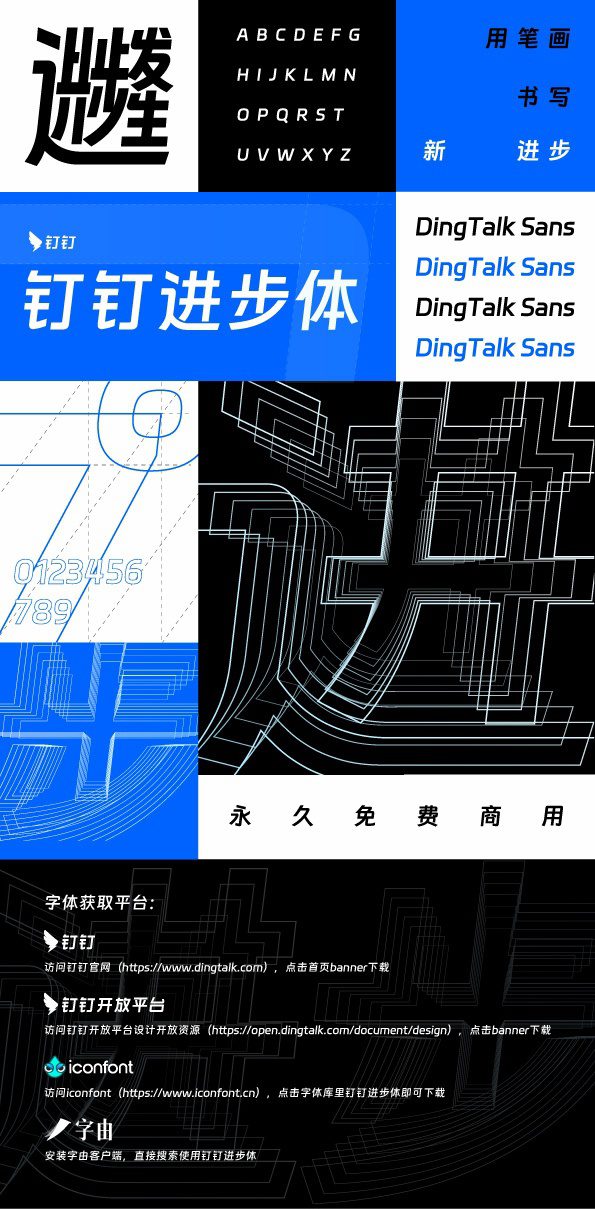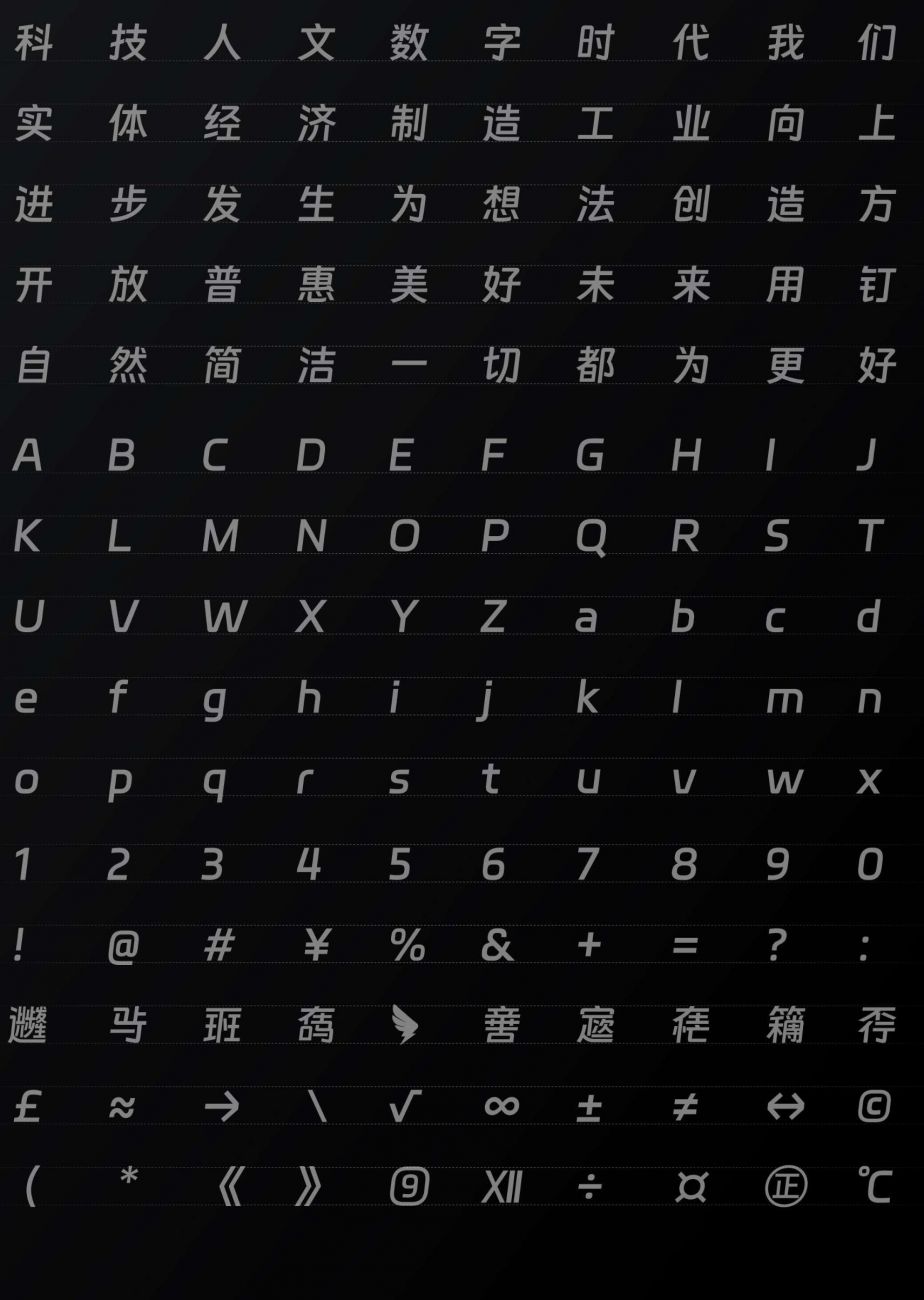
钉钉在杭州正式开启 7.0 版本产品发布会。发布会上,钉钉总裁叶军详细解读了钉钉 7.0 版本的新功能,同时推出了汉仪字库为其量身打造的定制字体“ 钉钉进步体 ”。
做自媒体和网站的朋友越来越多,使用的字体不小心就会有侵权的困扰,使用免费商用字体就可以自由自在啦,今天推荐一个好看的免费商用字体,「钉钉进步体」DingTalk JinBuTi。
钉钉进步体 涵盖了中、英文7526个字符,字体专为标题、美术字等场景而生,科技活力的同时兼具自然书写美感。
“钉钉进步体”以全新的视觉设计吸引用户注意力,令人耳目一新。同时,更具舒适感的字形笔画更好地展示了钉钉的数字科技感,传递出“让进步发生”的品牌新主张。
字体特点
钉钉进步体字体以7°做倾斜,弯钩笔画的弧度向上, 让整款字体年轻富有活力, 使其在标题场景应用时,更具特点和美感。结合最新钉钉品牌语言,在保持科技敏捷感的同时,希望字体可以更具人文温度,保持亲和不锐利,所以采用外圆内方的圆角处理方式,并对不同笔划的字体进行了简洁处理,既保正了笔划多的字能简洁不拥挤,又维持了笔划少的字体完整性,在既要优美感又要阅读感的情况下,做到了平衡。
钉钉进步体 字体展示